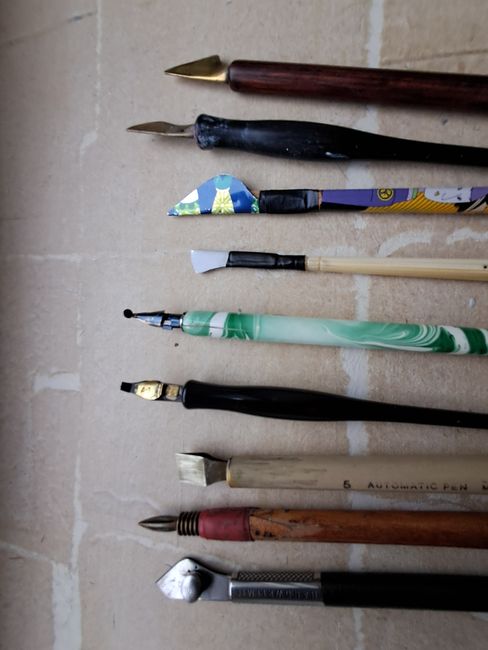
Pour finir l'année, un peu de sérénité avec un tableau de la série Autres Lieux.
Encres sur panneau de mdf enduit.
Pour la couverture, j'ai découpé et poncé deux plats de carton sans acide. Je les ai recouverts de papier Wenzhou marbré en suminagashi avec de l'encre japonaise. J'ai rencontré quelques difficultés d'ajustage lors du montage du leporello mais la qualité du papier à fibres longues m'a permis de m'y reprendre plusieurs fois.
Les imperfections se sont fondues dans le processus de réalisation et l'ont aussi nourri.
Vous ne verrez pas ce leporello au salon Anima Libri - Le livre et ses métiers d'art à Montreuil-Bellay en février prochain car aussitôt publié sur Instagram, il a été retenu.
![]() Dimensions fermé : 30,5 x 11 cm Feuille format A3 |
En février à Montreuil-Bellay (près de Saumur) j'animerai pour Anima Libri "Leporello calligraphié" à la suite du Salon du livre et ses métiers d'art". C'est un stage à la carte sur les outils contemporains avec un leporello calligraphié en réalisation finale. Suivre ce lien.
En mars, à Cherbourg, j'interviendrai pour l'association "Pleins de déliés" sur le thème "Matière & composition sur MDF". C'est un stage de peinture aux pigments.
En avril, je serai à Graçay dans le Cher, près de Vierzon. Je suis invitée à la troisième Biennale de Pluri-elles et pendant l'exposition j'animerai deux stages de calligraphie tous niveaux : "Suminagashi & calligraphie" et "Richesses de la plume square". Pour ces deux stages, je gère les inscriptions.
En juillet je reviendrai pour trois stages chez De Wereld Van Pixel à Bazel, près d'Anvers:
"1900, Belle époque de la lettre"
"Journal graphique - plume palette".
J'animerai aussi quelques stages à l'atelier de Kervoulouarn, à Plouarzel, à la pointe du finistère. Je ne suis pas chauvine, non non, mais je vous assure que c'est un endroit magnifique.
En février je propose d'explorer les possibilités de l'automatic pen sur deux jours :
"L'AUTOMATIC PEN, Entre écritures asémiques et alphabets graphiques"
En mars, le colapen sera à l'honneur avec :
"CAPITALE LIBRE AU COLAPEN"
Fin avril, je propose un stage de peinture, soit à mon atelier de Kervoulouarn, soit à Lampaul-Plouarzel :
MATIERE & COMPOSITION SUR PAPIER ENDUIT 2 JOURS en PAYS D'IROISE
Il est possible de programmer un stage à des dates selon nos convenances réciproques tout au long de l'année.
Je ne programme plus de stages pendant le dernier trimestre de l'année à mon atelier de Kervoulouarn. Cependant, il est toujours possible d'en organiser à la demande. Les thèmes sont disponibles dans les pages à gauche de ce blog ou en bas de la page "Workshops" de mon site.
* Si vous souhaitez offrir un stage, je peux vous calligraphier un bon cadeau, que j'expédie par voie postale ou numérique selon votre choix.
Les crédits - auteur et titre du texte - ont été posés avec une plume palette n°4.
J'ai fait une petite vidéo du leporello, visible sur mon compte Instagram.
Et quelques images :
La préparation du stage que j'animerai à Montreuil-Bellay juste après le salon me donne l'occasion de travailler des outils calligraphiques contemporains. Après avoir utilisé un automatic pen n°5 pour "L'horloge", je reste chez Baudelaire avec "Le soleil", calligraphié principalement avec une plume palette carrée, la speedball A, en taille 1 et 3.
J'ai employé l'encre ferrique du Calligraphe.com.